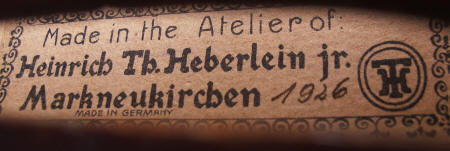
suche diese Schriftart (Geigenbau)
ich bin auf der Suche nach dieser Schriftart.  Ich weiss nicht ob es hilfreich ist, aber der Abdruck dieser Schrift ist ca 100 Jahre alt.
Das ist von Hand angefertigt und sieht eher graviert als gedruckt aus. Da dürfte jede Geige in Details unterschiedlich beschriftet sein.
ich finde das kleingeschriebene h bei dem antiken Schriftzug so schön